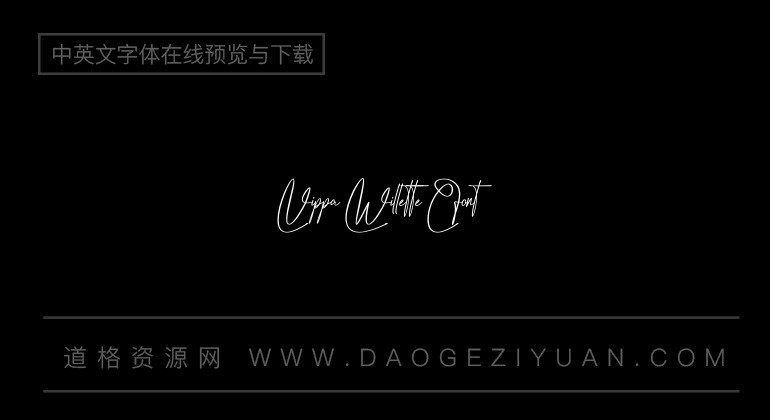
Vippa Willette Font
Vippa Willette Font 是一种装饰性手写体,具有优美且流畅的线条,给人一种优雅的感觉。该字体是由 Jessica McCarty 设计的,用于个人或商业用途。它适合用于宣传册、海报、贺卡、书籍封面等设计项目。这种字体的优点是易于阅读,具有良好的可读性和易用性,尤其适合用于标题和短语。它有两种版本,一种是带有细节的手写字体,另一种是精简版的字体,适合需要更清晰、更整洁的设计项目。总的来说,Vippa Willette Font 是一种非常适合设计师和创意人士使用的字体。
Vippa Willette Font是一款非常不错的手写艺术字体,具有很好的视觉感,适合于文化类的宣传设计、商业类品牌的广告和产品包装设计以及个性化文字排版等较多场景。